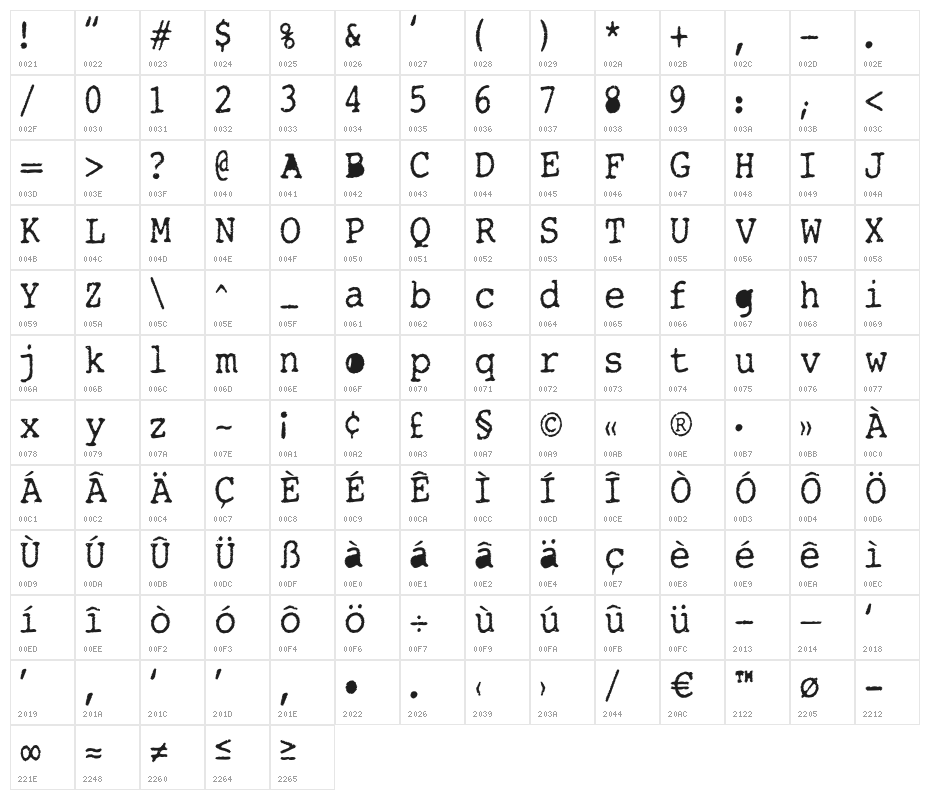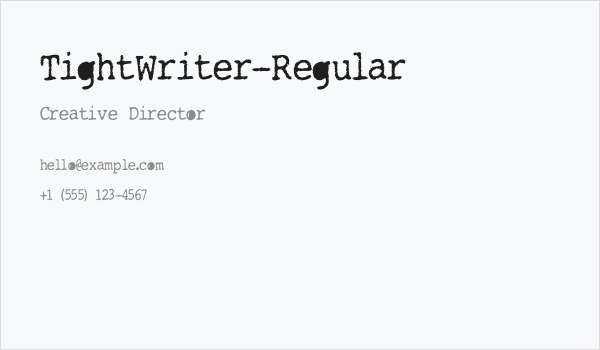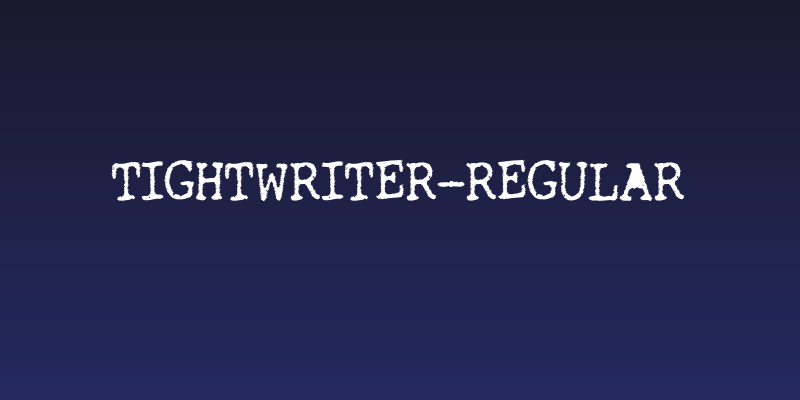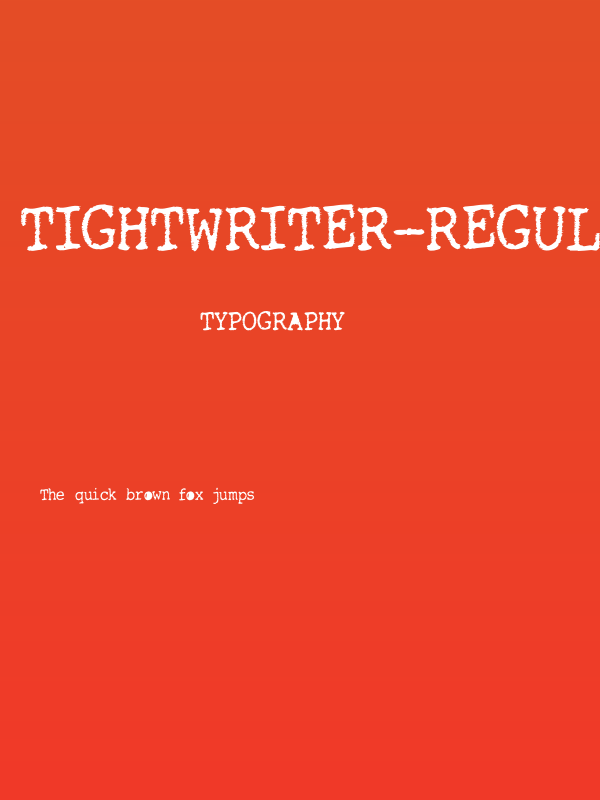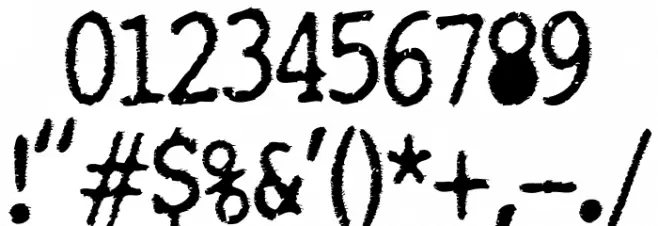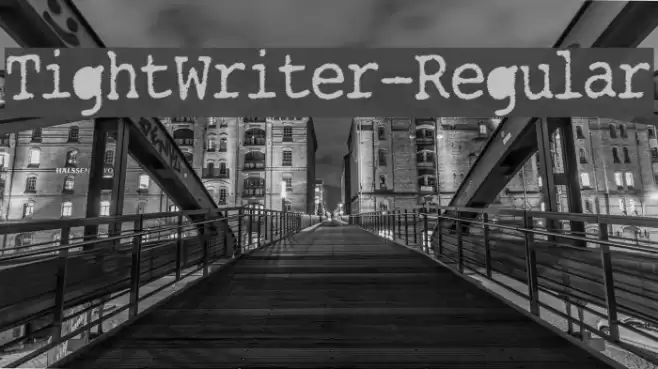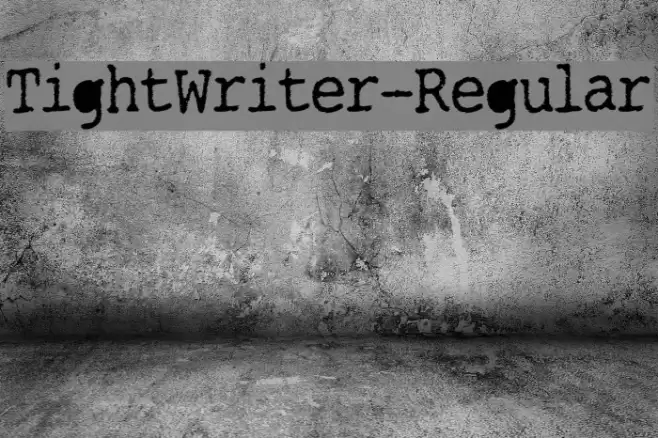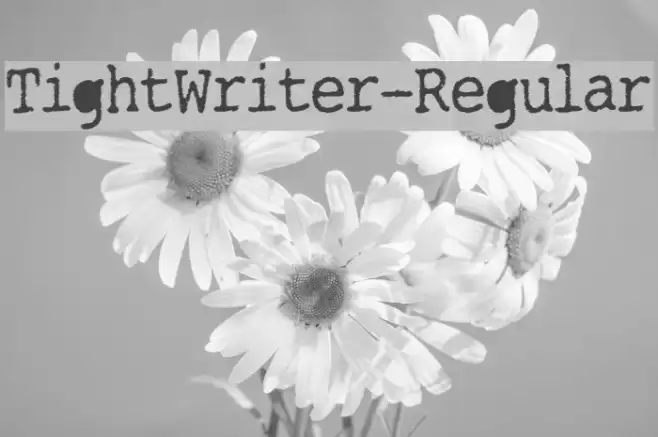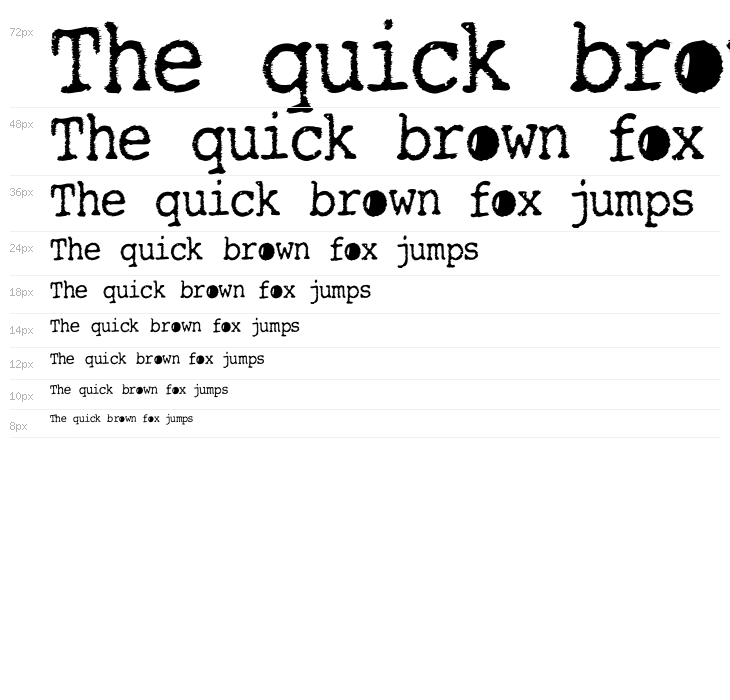
TightWriter-Regular Font
✎ Typewriter
| 名前 | TightWriter-Regular |
| フォントファミリー | Tight Writer |
| カテゴリ | Typewriter |
| 用途 | Headlines, Logos, Decorative text |
| おすすめプロジェクト | Ideal for vintage-themed designs, retro posters, book covers, and branding that requires a nostalgic touch. |